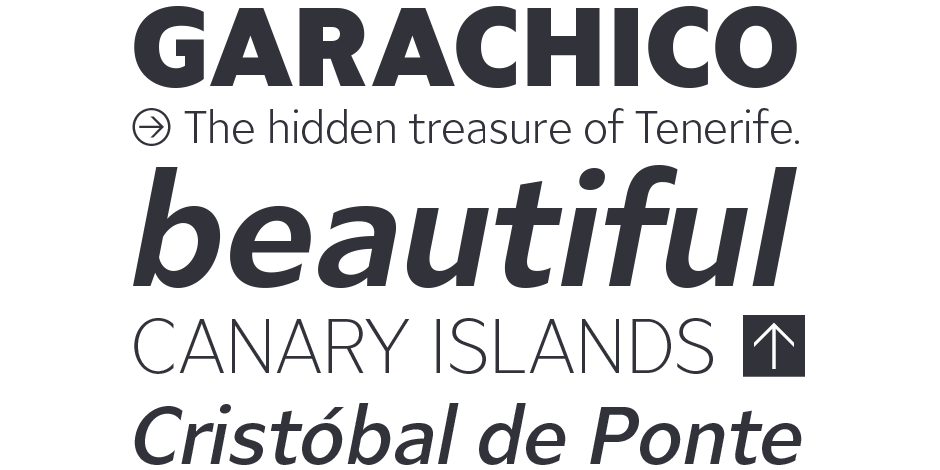
Ardena Fuente Guía de campo
Buenas prácticas
Ardena puede utilizarse tanto de forma sobria como expresiva. La amplia selección de estilos la hace adecuada tanto para titulares contundentes como para textos extensos. Su amplia colección de caracteres la convierte en un auténtico caballo de batalla. Es un todoterreno versátil que está a la altura de todos los retos: para identidad corporativa, editorial, branding, sistemas de orientación y guía y mucho más.
Familia Ardena
Familia
Ardena es una moderna familia tipográfica sans-serif y tiene un total de 20 estilos, de fino a pesado y cursivas a juego. Aunque neutra y clara a primera vista, puede caracterizarse como agradable y segura de sí misma gracias a sus formas abiertas y redondeadas y a sus terminales verticales.
Fuente Hechos
• La familia Ardena tiene un total de 1064 glifos por fuente, que incluyen toda una gama de características como más de 200 idiomas, versalitas, números, flechas, símbolos, alternativos y muchos más.
• Ardena dispone de una amplia gama de números circulares y cuadrados. Gracias a Open Type Features y a un sencillo sistema, los distintos diseños también pueden "escribirse" de forma sencilla sin tener que seleccionarlos primero en una paleta de glifos.
Raíces
La principal motivación de Julien Finckers para crear Ardena fue diseñar una sans serif de bajo contraste, neutra y versátil. De las que ya hay miles, pero él simplemente quería dibujar su propia interpretación. En cuanto al carácter, Ardena debía parecer agradable y segura al mismo tiempo. Entre otras cosas, Julien esperaba esto de las formas abiertas y redondeadas y las terminaciones verticales. El proceso de diseño de Ardena duró unos seis meses hasta su lanzamiento en febrero de 2021.
Ardena-Tipografía
Legibilidad
Los pesos fino y grueso son especialmente adecuados para titulares contundentes, mientras que los pesos medios pueden utilizarse para retos tipográficos y cuerpo de texto. La gran altura x, el bajo contraste y las aperturas abiertas proporcionan una gran legibilidad tipográfica.
Cómo detectar a Ardena